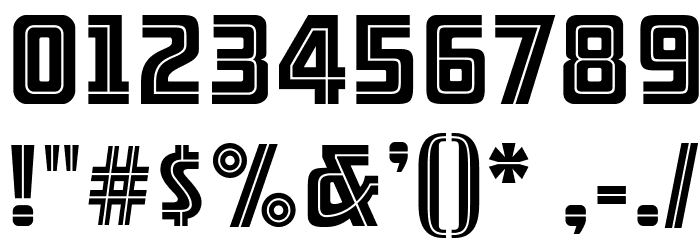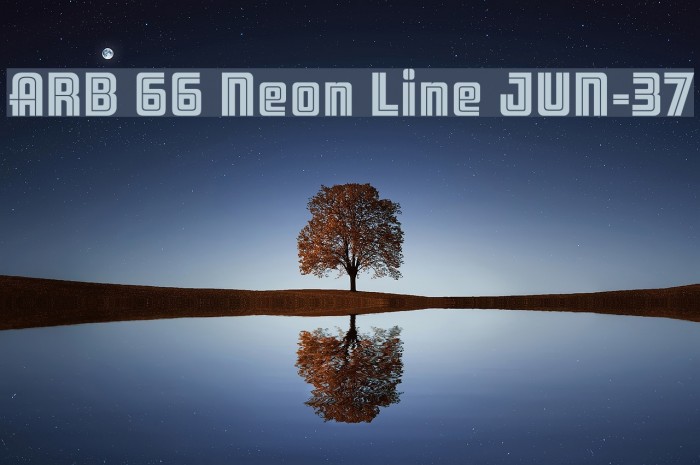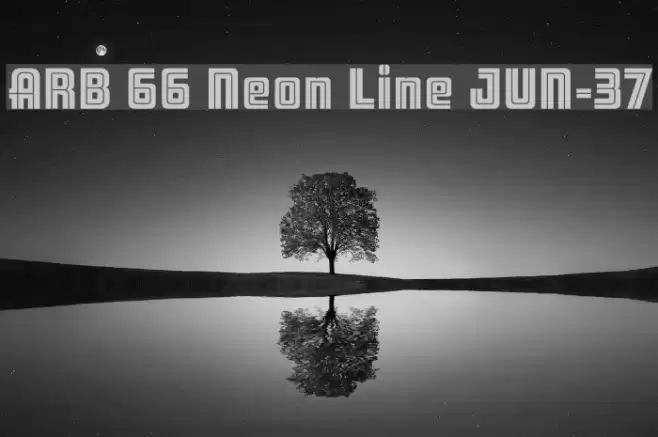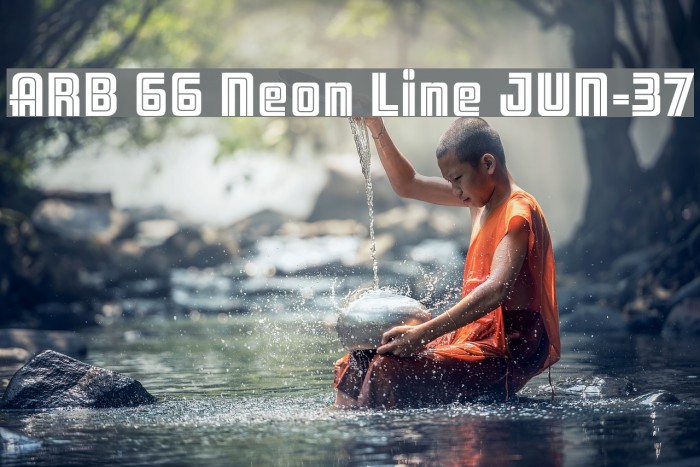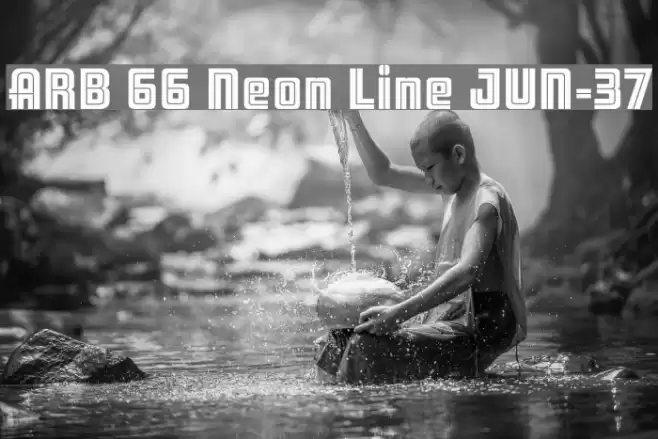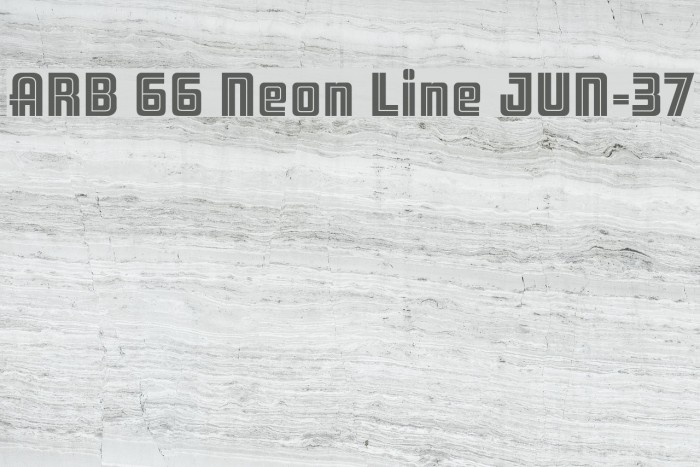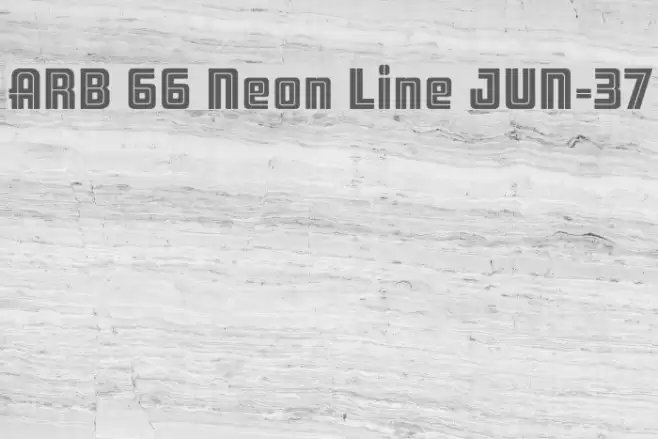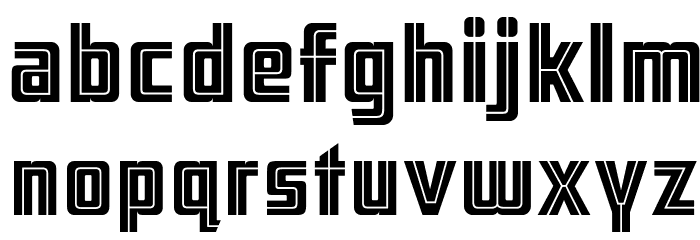
ARB 66 Neon Line JUN-37 Font
✎ Outline
| Projetos propostos | Ideal for projects requiring a futuristic or tech-inspired look, such as digital interfaces, video game graphics, or sci-fi themed posters. |